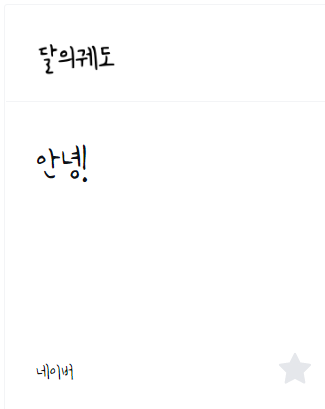
이모티콘 만들 때 상업적 이용 가능 무료 폰트 추천 17개
이모티콘을 만들 때에 그림을 그리기도 하고 알맞은 글을 써넣기도 하는데 그곳에 직접 글을 써도 좋지만 상업적으로 이용이 가능한 폰트를 사용해도 된다.
이모티콘 만들 때 혹은 기타 상업적으로 이용할 때 이쁜 이모티콘을 골라보았다.
상업적 무료 폰트 추천 10개
1. Gmarket Sans M
2. Gmarket Sans B
3. 배민 주아체
4. 한나체Pro
5. 배민 도현체
6. 중학생
7. 바른히피
8. 카페24 동동
9. 동글Bold
10. 수줍은 대학생
11. 하나손글씨
12. 느릿느릿체
13. 장미체
14. 달의궤도
15. 미니 손글씨
16. 또박또박
17. 둘기마요Medium